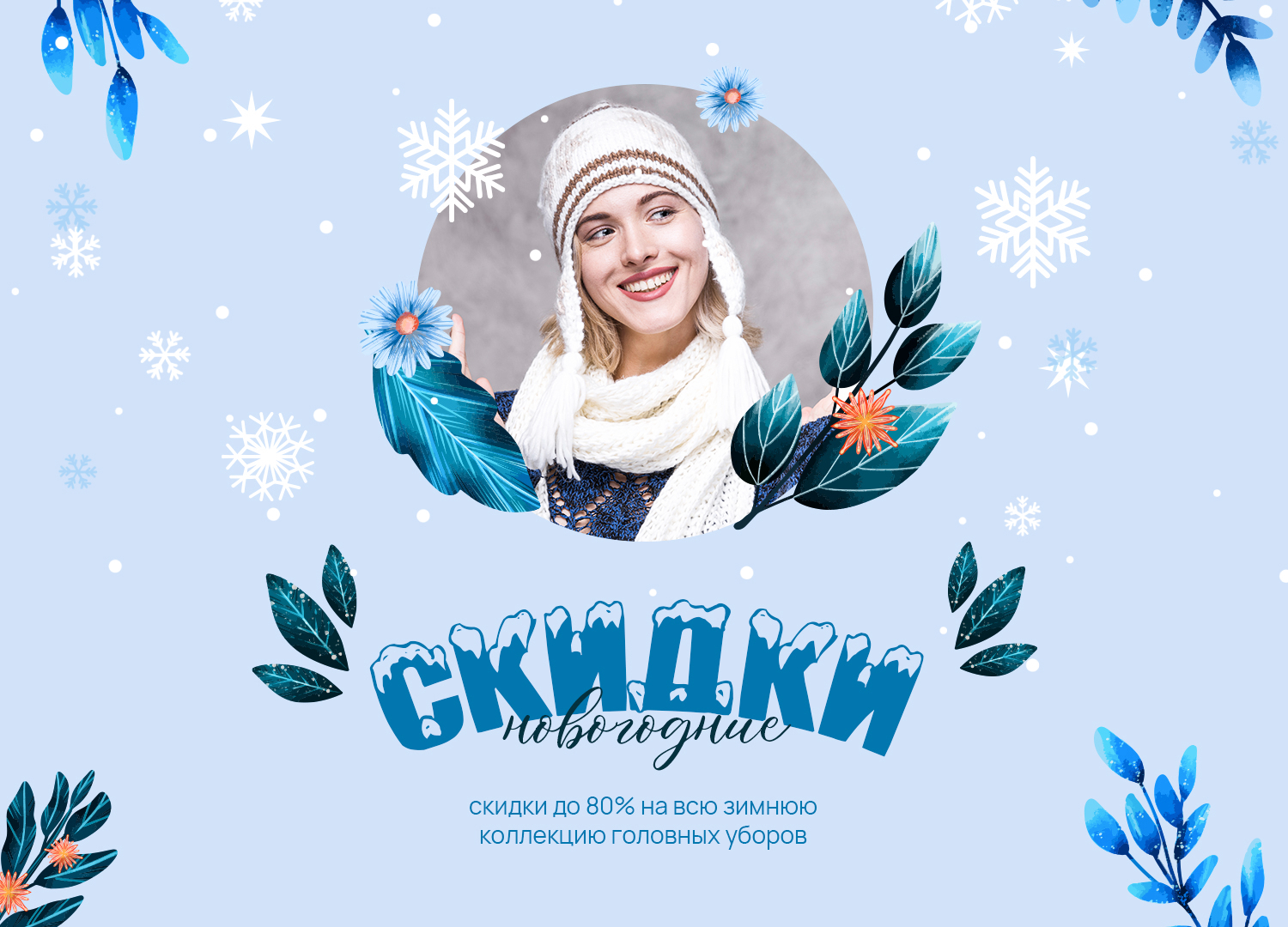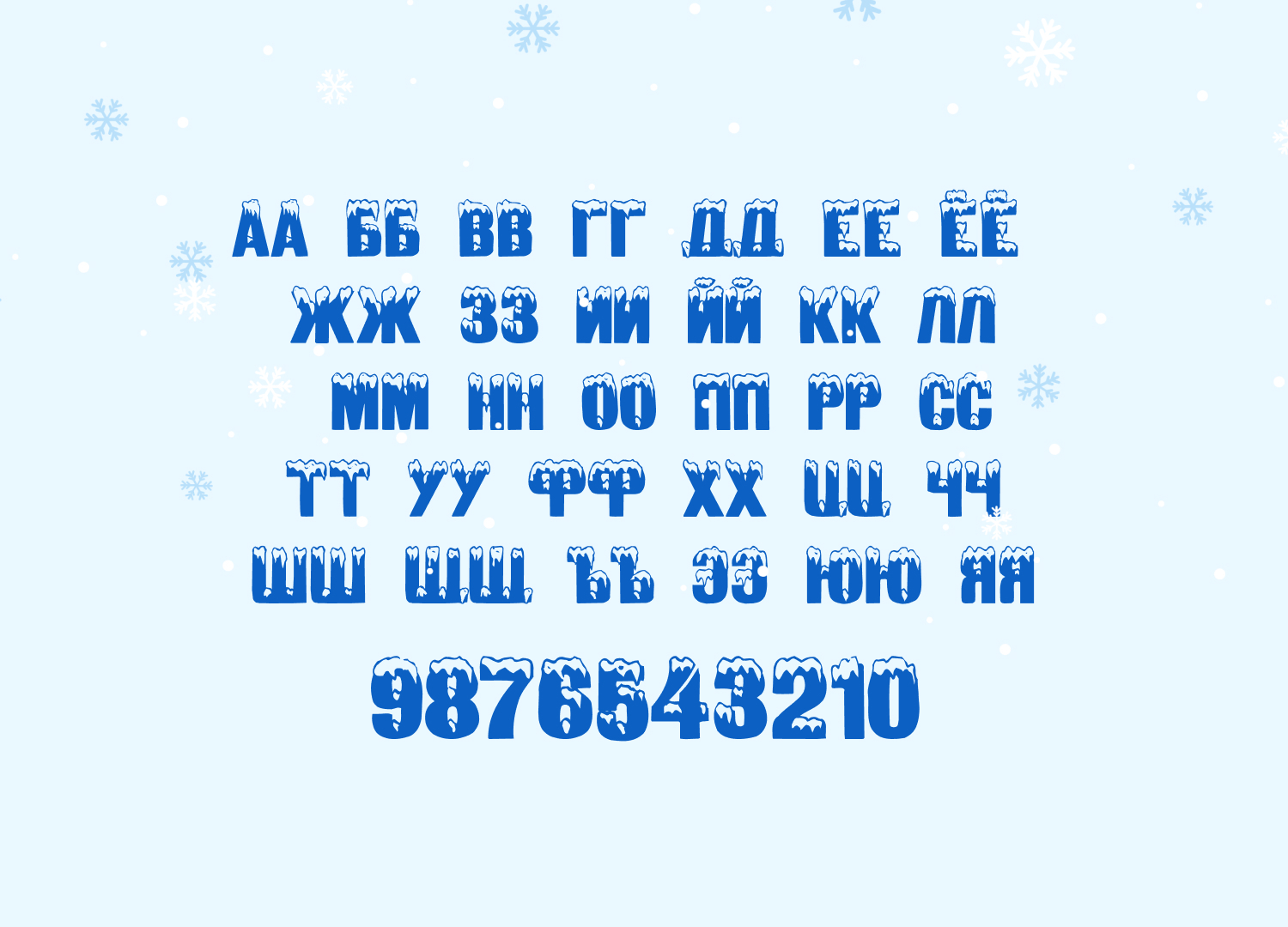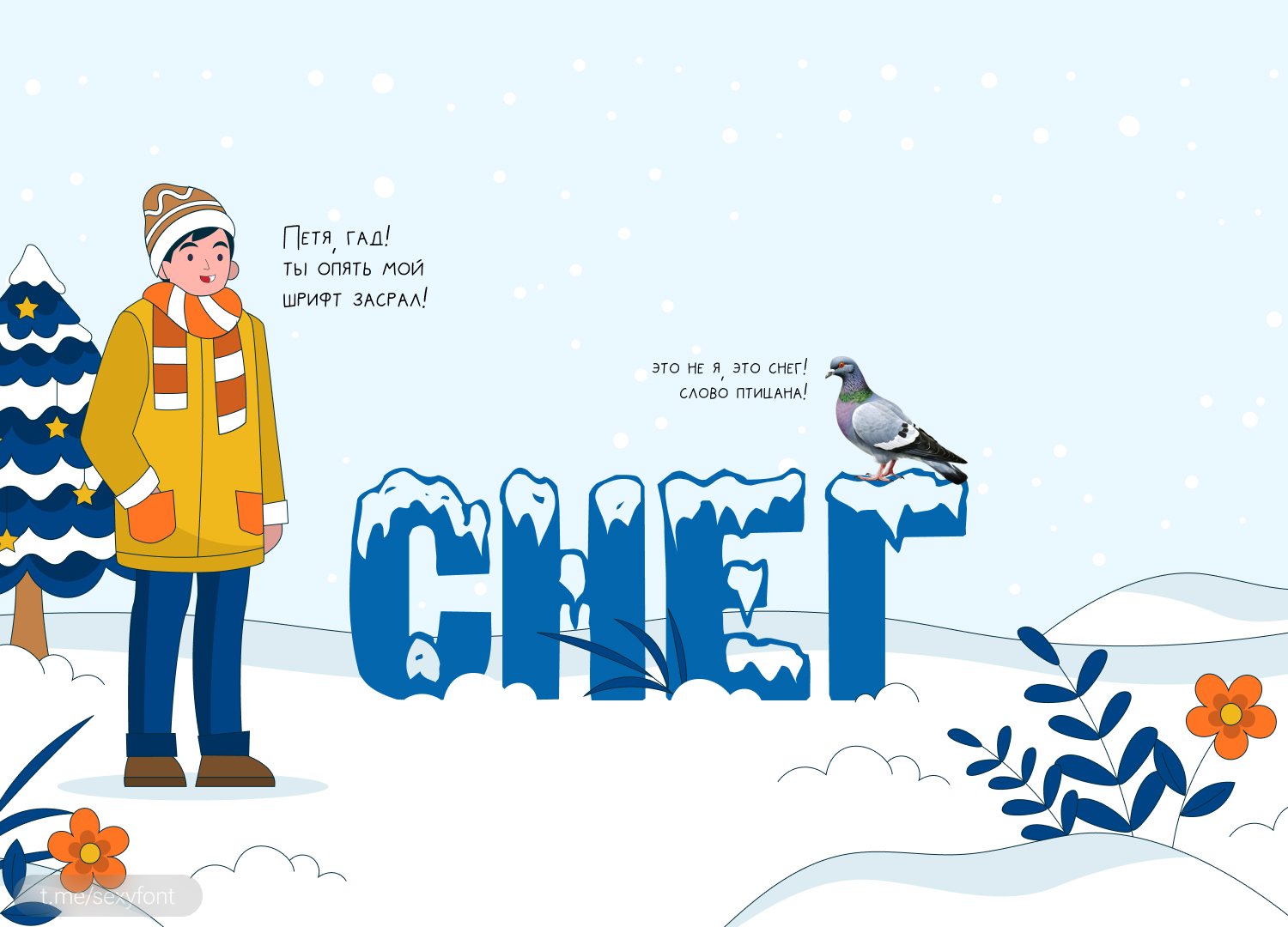
Занесенный. Снежный шрифт для новогодних проектов
Очень старенькая новогодняя классика) Думаю им еще дед мороз в 19 веке стихи писал. Но тем не менее решил сделать для него презентацию. Раньше этого никто не делал.